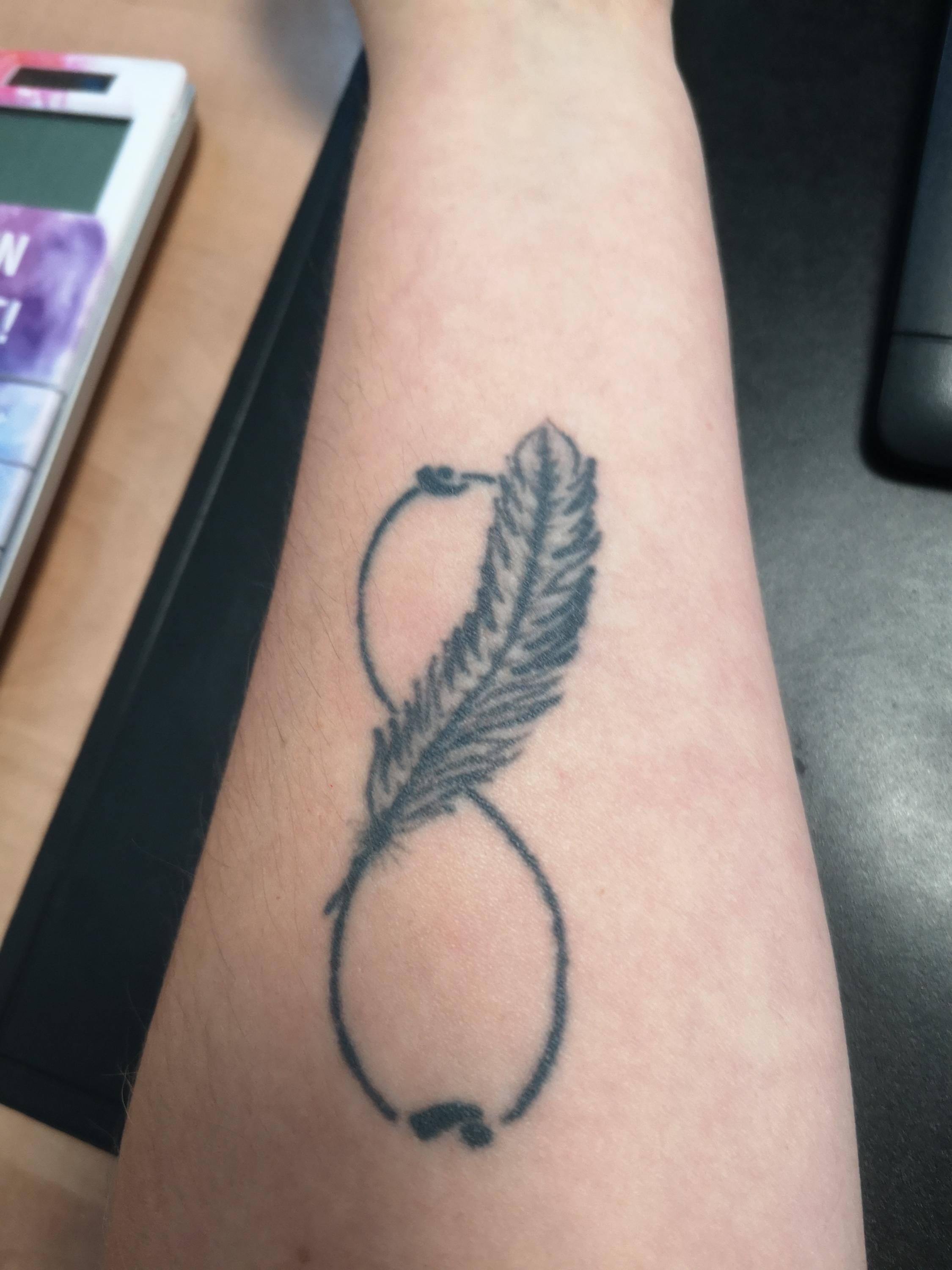
Suche Schriftart die auf dem Tattoo sichtbar ist
kann mir vielleicht jemand sagen was das für eine Schriftart ist? Links ist der Buchstabe "J", Rechts ist der Buchstabe "P".
Das Alphabet hat in jedem Buchstaben irgendwo einen Punkt.